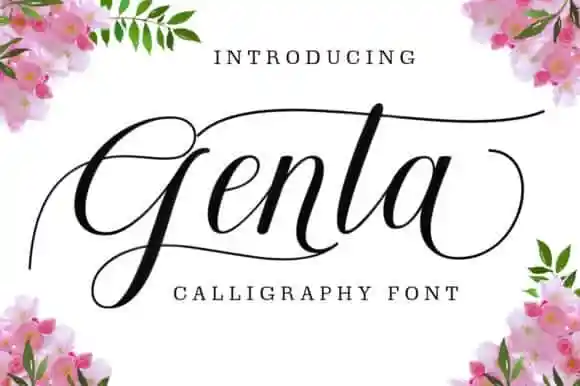
Genta Calligraphy Font – Download Grátis
Genta Calligraphy Font é uma elegante e delicada tipografia escrita a mão, perfeita para quem valoriza estilo feminino. Esta fonte apresenta alternativas de caracteres divididas em várias características Open Type como Swash, Sets Estilísticos, Alternâncias Estilísticas, e Alternâncias Contextuais. Ela possui codificação PUA, permitindo que você acesse facilmente todos os gílios e swashes. Característica deste design é uma base variável, linhas suaves, belas formas e alternativas de escrita incríveis. Genta mantém suas influências clássicas da caligrafia enquanto se sente contemporânea e atualizada. Descubra por que amamos esta fonte e faça do seu projeto algo realmente especial!